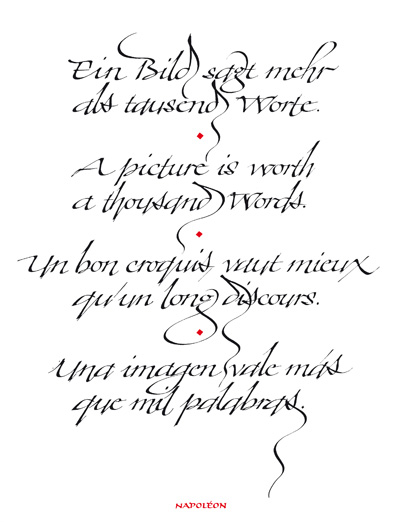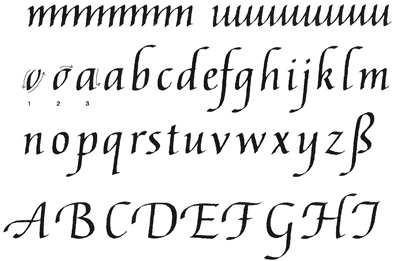
Offenes Atelier
mit Katharina Pieper
Das offene Atelier dient der Vertiefung bereits erlernter Schriften. In ruhiger kalligrafischer Atmosphäre kann jeder, der bereits einen oder mehrere Kurse besucht hat, teilnehmen und erhält individuelle Hilfestellung.
Sütterlin, deutsche Schrift, Kurrentschrift
Kursleitung: Brigitte Jenner
Erfahrene im Umgang mit Schrift als auch Einsteiger oder noch nicht allzu weit Fortgeschrittene finden in diesem Tageskurs Anleitung für die jahrhundertealte Kurrentschrift, die Handschrift Goethes und Vorläuferin der Sütterlin- und deutschen Schrift. Die Unterschiede dieser Schriften werden erklärt und die wichtigsten Merkmale gezeigt. Die Schriften werden mit Spitzfeder oder Bandzugfeder geschrieben.
Freie Heftungen und japanische Buchbindetechniken
Kursleitung: Sascha Boßlet
Grundkurs/Aufbaukurs
Dieser Kurs ist geeignet für alle, die einfache Buchbindetechniken kennenlernen möchten. Sowohl Neueinsteiger als auch bereits Erfahrene finden hier gute und professionelle, individuelle Anleitung.
Feder, Tinte und Papier
Kursleitung: Ilse Spies
Grundkurs
Ein Hereinschnuppern in die Welt der Kalligrafie. Einige typische Kalligrafie-Federn wie Bandzugfeder, Redisfeder und Spitzfeder werden in diesem Tagesworkshop kennengelernt, dazu die Schreibflüssigkeiten Tinte, Tusche und Gouache. Verschiedene Papiersorten können beschrieben und mit den Federn ausprobiert.werden. Sowohl die eigene Handschrift als auch einfache kalligrafische Schriften werden vorgeführt und geübt. Dieser Kurs richtet sich auch an Jugendliche.
Die englische Schreibschrift
Kursleitung: Katharina Pieper
Aufbaukurs
Dieser Kurs richtet sich an diejenigen, die bereits mehrere Workshops zur englischen Schreibschrift besucht haben. Klein- und Großbuchstaben werden vertieft und das Gestalten eines längeren Textes angegangen.
Einführung in die Kunst der arabischen Kalligrafie
Kursleitung: Ayham Najjar
Grundkurs/Aufbaukurs
In diesem Workshop wird zunächst das arabische Alphabet, das von rechts nach links
geschrieben wird, erklärt. Mittels speziell zugeschnittener Rohrfedern werden Bewegungsablauf, Schreibrhythmus und Möglichkeiten der Verbindung einzelner Buchstaben gezeigt. Der Dozent zeigt ein einfaches sowie ein kalligrafisches Alphabet. Einzelne Worte oder kurze Gedichte können im Anschluss kalligrafisch geschrieben werden. Am Ende des Workshops wird ein farbiger Hintergrund angelegt, auf dem Worte und Sätze aufgetragen werden.
Civilité – von der schwungvollem mittelalterlichen Schrift zur Druckschrift
Kursleitung: Katharina Pieper
Aufbaukurs
Die Civilité ist eine gebrochene Schrift, die in Frankreich von dem Typografen Robert Granjon in Lyon um 1557 ursprünglich als Druckschrift geschaffen wurde. Sie bietet interessante Formen und viel Anregung zum Erweitern des Formrepertoires, denn sie zeichnet sich durch das Spannungsverhältnis zwischen niedrigen Kleinbuchstaben und sehr kalligrafischen, ja waghalsigen Schwüngen bei den Großbuchstaben aus. Das Alphabet hat Ähnlichkeiten
mit der Bastarda und wird sehr selten unterrichtet.
Humanistische Kursive für Einsteiger
Kursleitung: Katharina Pieper
Grundkurs/Aufbaukurs
Dieser Kurs ist sowohl ein Einstieg ins kalligrafische Schreiben, aber auch für diejenigen geeignet, die bereits Kurse zur humanistischen Kursive besucht haben. Klein- und Großbuchstaben, Wortgestaltung und einen kurzen Text schreiben sind Hauptthema
dieses Kurses.
Katharinas kalligrafische Trickkiste
Kursleitung: Katharina Pieper
Aufbaukurs
Auf mehrfache Nachfrage ergab sich dieser Kurs, in dem Tipps und Tricks verraten werden, die für die kalligrafische Gestaltung wichtig sind: Korrekturmöglichkeiten, Textgestaltung, Linien ziehen leicht gemacht, einfache Hintergrundgestaltung u.v.m.